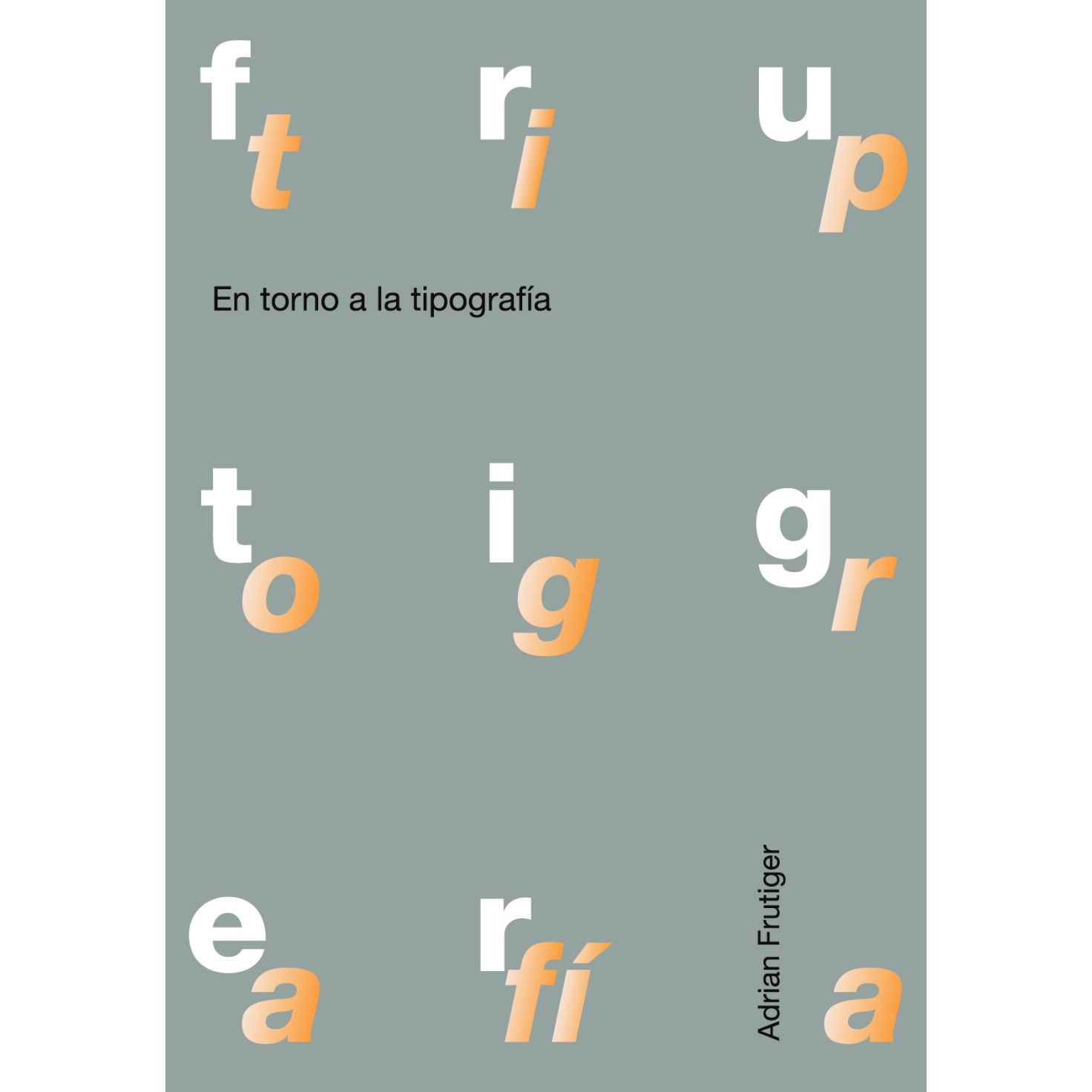
En torno a la tipografía
Adrian Frutiger repasa algunos temas básicos que hay que conocer, como el origen de la escritura y su evolución, la aparición de los caracteres tipográficos y su evolución formal, influida por la de las técnicas de impresión; y el proceso de lectura, los criterios de legibilidad y las diferentes maneras de leer; o las reglas que hay que seguir para crear una familia de letras.
Da un repaso también a las grandes familias de tipos y presenta algunos de los que él ha creado, con objeto de explicar, concretamente, lo que han aportado a la tipografía y extraer de ello sus enseñanzas. Aborda, así, la epopeya de la Univers (el desarrollo de sus veintiuna series previsto desde la concepción misma, algo nunca visto en la historia de la imprenta), el Roissy (para la señalización del aeropuerto de Roissy-Charles-de-Gaulle, carácter que más tarde se convertiría en el Frutiger), el OCR-B (carácter de reconocimiento óptico para ordenadores que pasó a ser un estándar internacional [1972] en el ámbito bancario) y, por último, la adaptación a las técnicas contemporáneas de composición y reproducción de un tipo de letra no latino, perteneciente a una cultura totalmente distinta de la nuestra: el Devanagari (procedente del sánscrito), que constituye la escritura oficial de la India. Para acabar este recorrido, el autor habla sucintamente de la creación de logotipos.
Contenidos:
Introducción
Enseñar y aprender, el camino de la invención
Las grandes familias de tipos de letra
El proceso de lectura
La concepción de un tipo
Los tipos de letra diseñados por Adrian Frutiger
Concebir un logotipo
Epílogo
El adulto tiene la responsabilidad de transmitir su saber, sus habilidades. No es una obligación, sino un instinto profundo del que nace la paciencia para aceptar la cotidiana presencia de los jóvenes a su lado. Este instinto le lleva a hacerles oler, sentir, ver, amar el material; le empuja a enseñarles la preparación y el manejo de los utensilios; le incita a transmitirles la perseverancia, la necesidad de esforzarse una y otra vez, le induce a enseñarles cómo concebir y desarrollar una nueva obra.
A. Frutiger
Gracias a esta intimidad del trabajo en común, generación tras generación, igual que en una cadena, el saber y la habilidad siguen transmitiéndose, creciendo y abriéndose al futuro.
El saber y la habilidad que poseemos hoy constituyen la base del mañana. La obra actual, profundamente arraigada en todas las actividades del pasado humano, constituye el fundamento de la obra por venir.
Acceder«Este libro resulta relevante porque acerca el punto de vista de uno de los más reconocidos tipógrafos de nuestro tiempo a las nuevas generaciones, a la vez que introduce de forma didáctica y amena temas en los que éstos tendrán que profundizar a lo largo de su formación si quieren convertirse en unos buenos profesionales de este ámbito.» (Arnau Estela, monográfica.org, 10/2012)